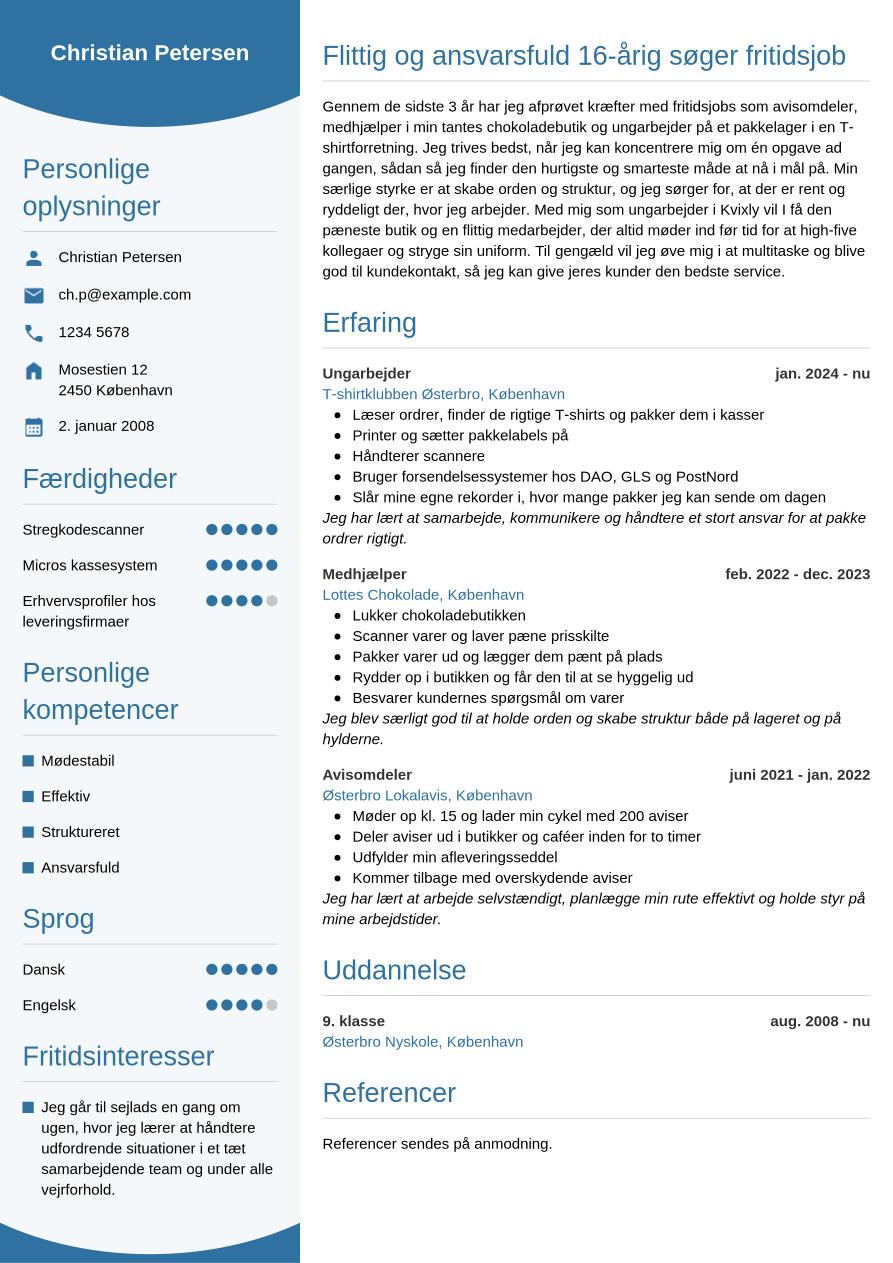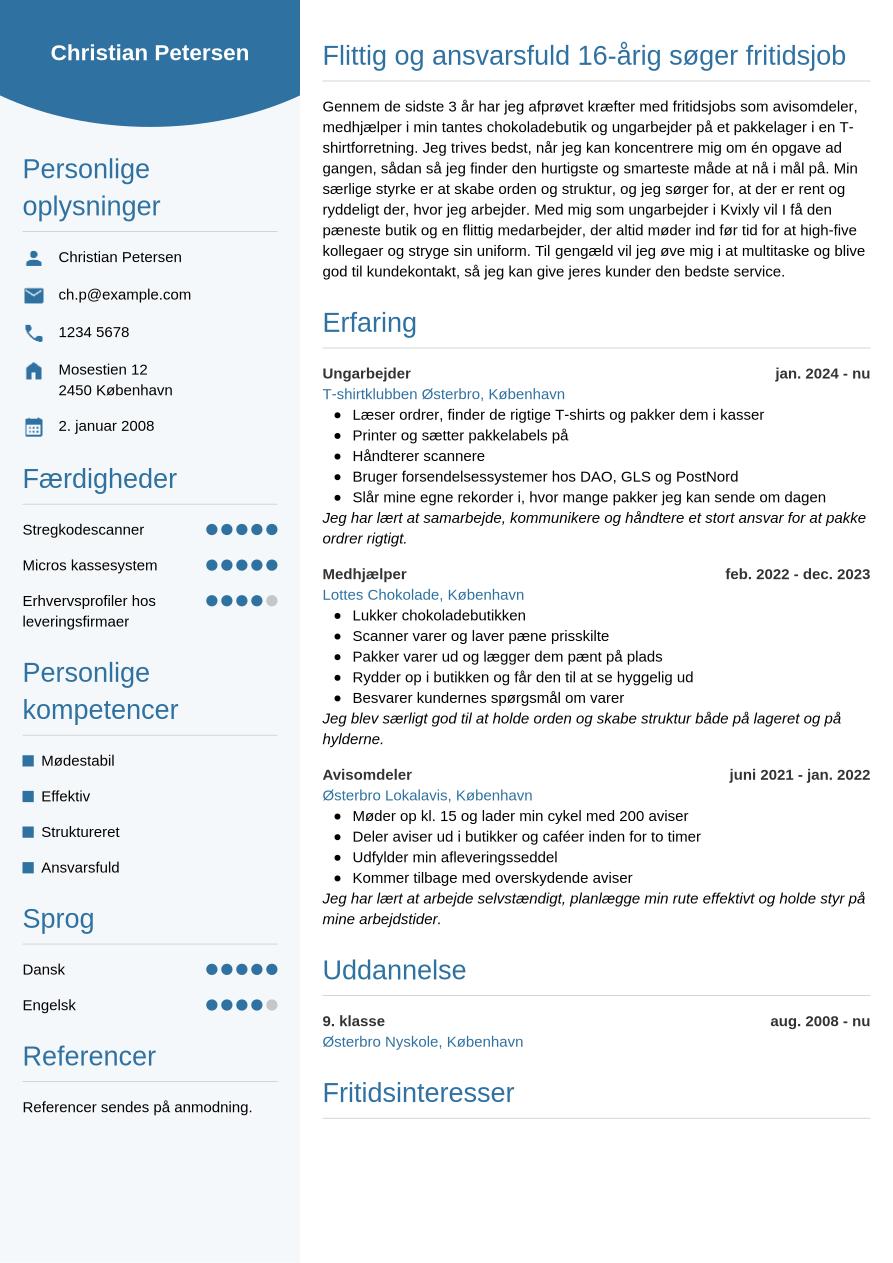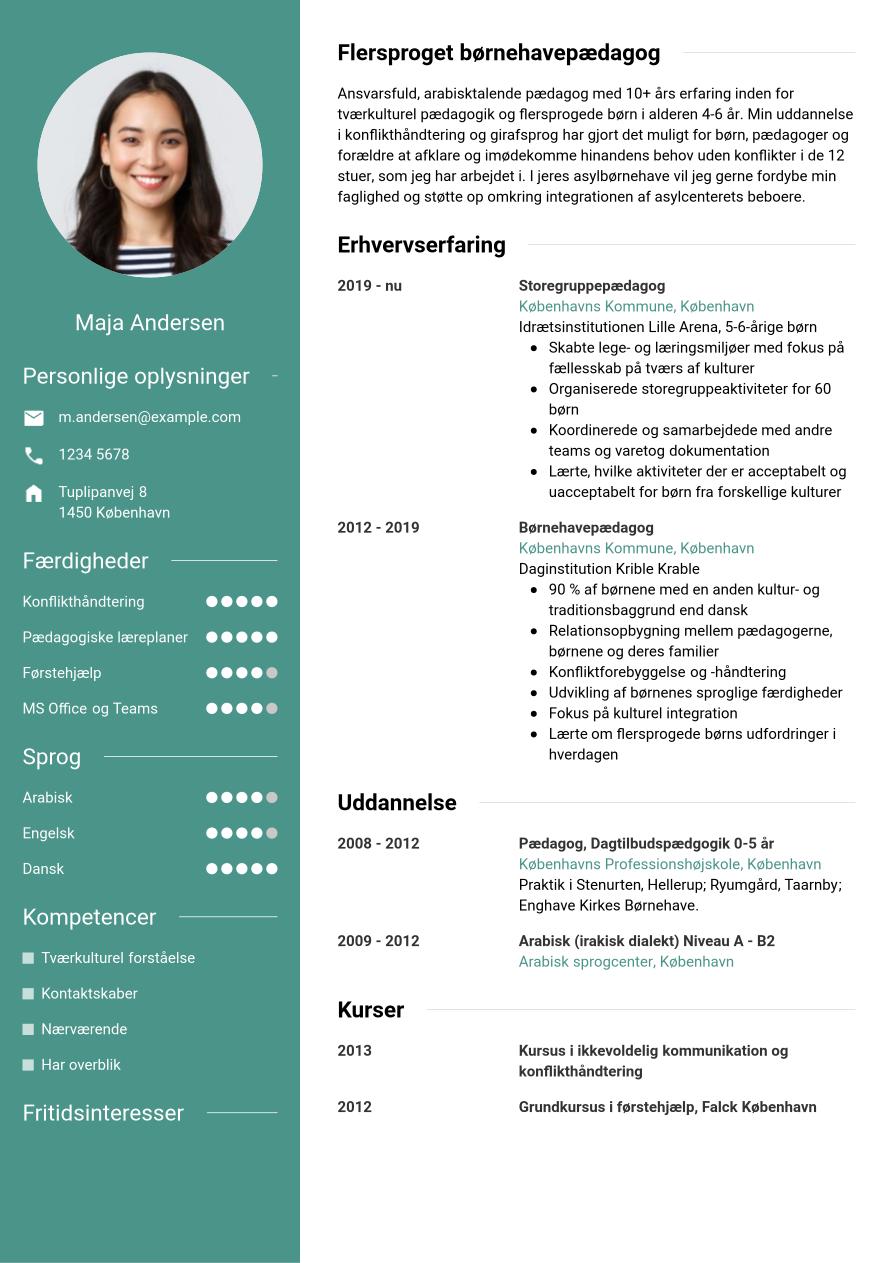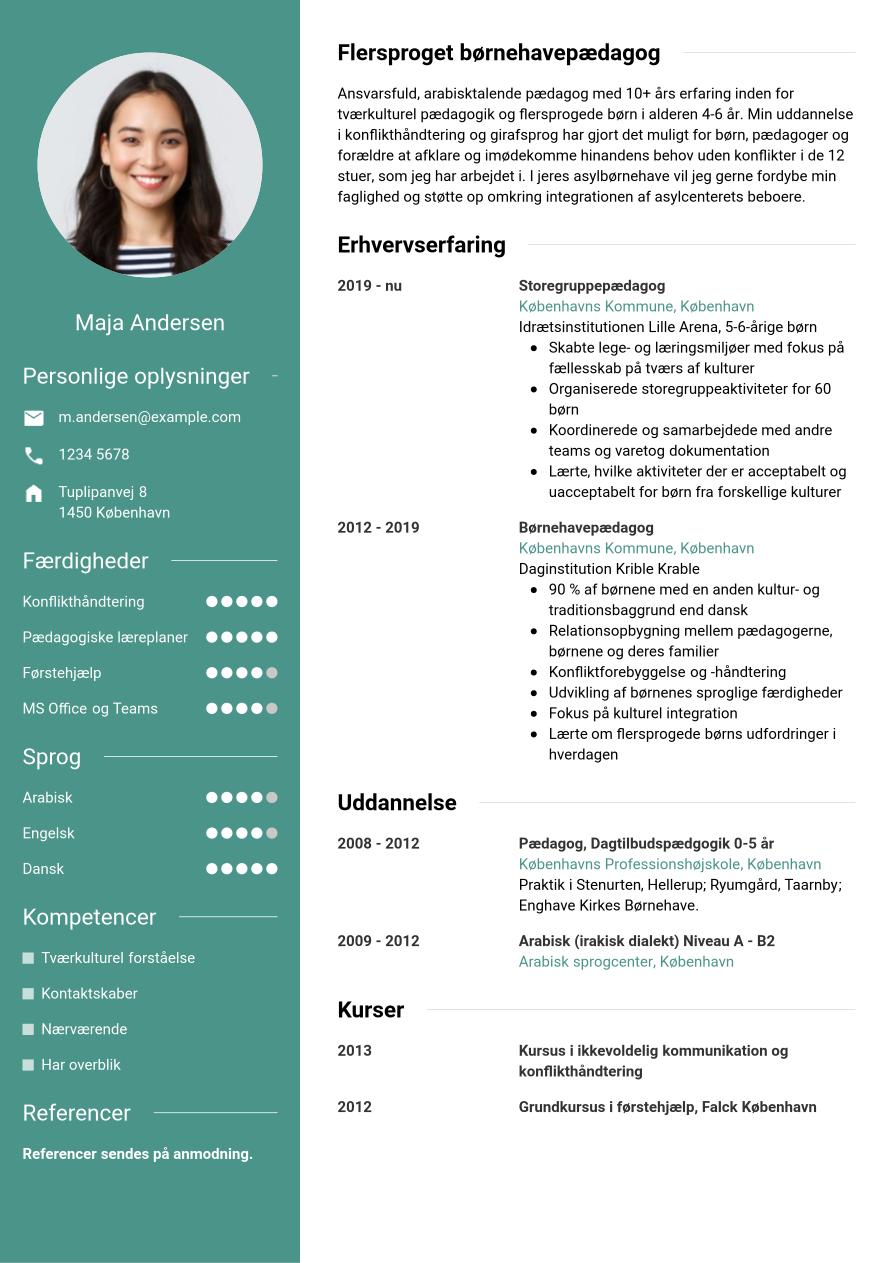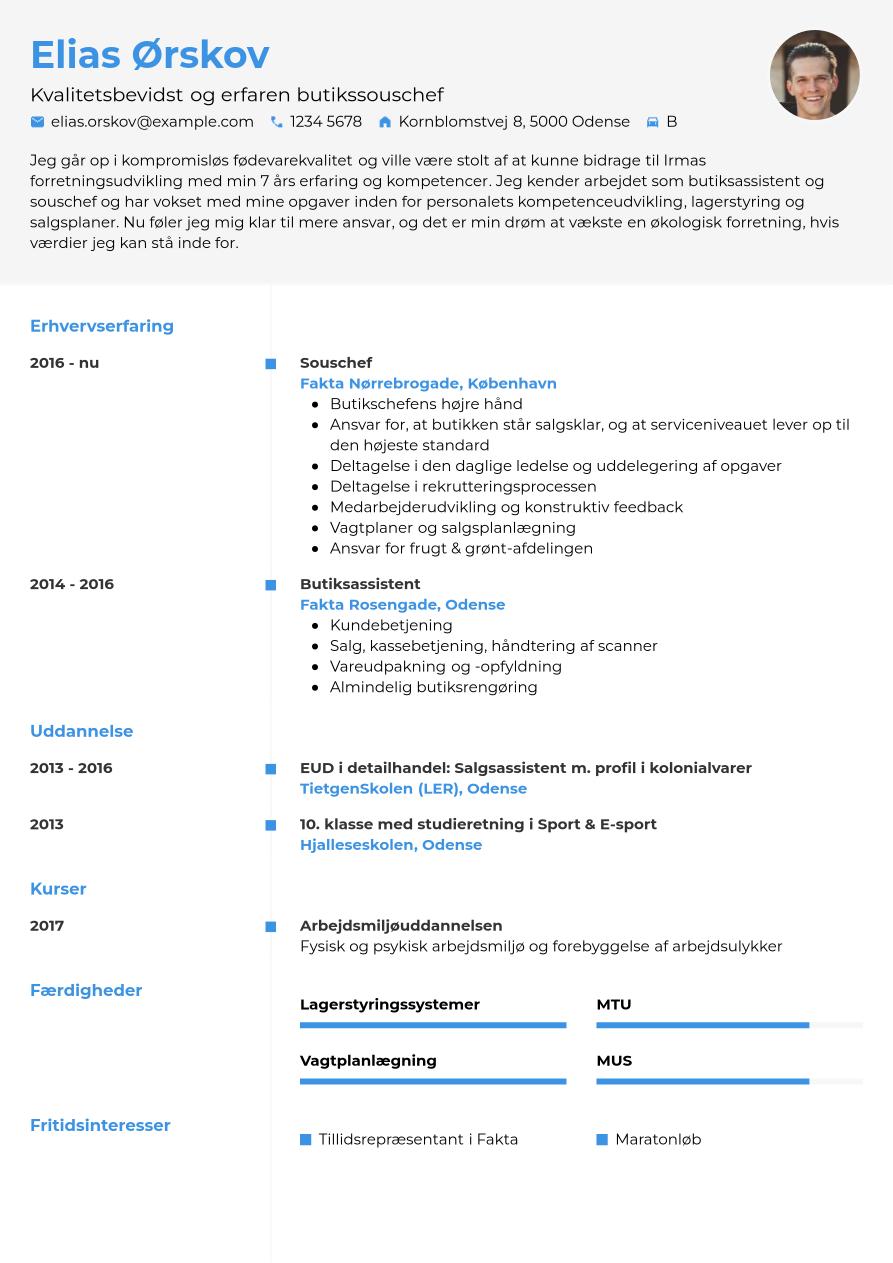
CV-skrifttype: de bedste CV-fonte og typografi
Når du skriver et CV, er der en del overvejelser, som du skal gøre dig omkring typografien. Skrifttypen og skriftstørrelsen samt brug af fremhævninger med blokbogstaver, kursiv eller fed skrift kan gøre ethvert CV kaotisk og svært at læse. På den anden side, hvis du bruger dem fornuftigt og følger nogle simple retningslinjer, kan det forbedre CV’ets læselighed og øge dine chancer for at komme til en jobsamtale. I denne artikel kigger vi på fonte til CV’et samt andre grafiske og typografiske muligheder, du bør overveje, hvis du vil skrive et CV, der virker.
Typografi i CV’et
Når du skal vælge en skrifttype til CV’et, er der to skriftfamilier at vælge mellem: Serif (med ”fødder”) og sans-serif (uden ”fødder). Seriffer er de små linjer, som du kan se under og ved kanterne af bogstaverne i skrifttyper som Times New Roman. Fonte i familien sans-serif er uden de små streger – som den, du læser nu. Når du skriver et CV, bør du vælge én skrifttype, og lave hele CV’et med den. Forskellige skrifttyper skaber nemlig et kaotisk indtryk og trætter læserens øjne.
Serif-fonte til et CV
Serif-fonte er designet med ”fødder” for at øge læsbarheden, når man printer teksten og læser den på papir. Den form for font gør det lettere for læserens øjne at flugte med teksten, og linjerne bliver klare. Disse skrifttyper står i høj kontrast med en hvid, ikke-lysende baggrund. Derfor bliver de brugt i aviser og magasiner, og du kan med fordel bruge dem til printede CV’er. Hvis du gerne vil bruge en serif-font, men er usikker på, om din arbejdsgiver vil læse CV’et digitalt eller på papir, så kan du med fordel bruge skrifttypen Georgia. Den er designet til digital brug.
Sans-serif skrifttyper til et CV
Skrifttyper fra familien sans-serif er åbne og nemme at læse på en skærm. De ser lettere ud, og serifferne forstyrrer ikke øjet, når det hvide baggrundslys fra skærmen skinner bag bogstaverne. Hvis du skal sende dit CV digitalt, så anbefales det at bruge sans-serif-skrifttyper, såsom Arial, Calibri, Verdana, Tahoma og Trebuchet.
Skriftstørrelse på CV
Hvis dit CV skal være nemt at læse, så bør du vælge maksimalt 3 skriftstørrelser af den samme skrifttype: En til overskrifter, en til underoverskrifter og en til brødteksten. Bruger du en åben skrifttype, så kan du med fordel vælge disse skriftstørrelser:
- Maksimalt 16 til overskrifter
- Maksimalt 13 til underoverskrifter
- Maksimalt 11 til brødteksten
Skriftfarve til CV’et
Brug 1 – 2 skriftfarver i et CV, hvis din baggrund er hvid. Den ene farve er til overskrifter, underoverskrifter og brødteksten, og den anden (en lysere skriftfarve) er til de tilfælde, hvor du har to underoverskrifter efter hinanden (se eksemplet i afsnittet om kursiv). Hvis du laver dit CV med margener i en mørkere farve, skal du bruge en tredje skriftfarve til at stå i kontrast med den mørke baggrund. Vælg en hvid eller lysegrå skriftfarve, eller en meget lys tone af dit CV-layouts dominerende farve.
Skrifttypen og kontrast
Da et CV skal fylde maksimalt 2 sider, udnytter man også margener i CV’et for at indsætte vigtig information. Det kan være dit CV-foto, personlige oplysninger, hårde færdigheder, bløde færdigheder samt faglige og personlige kompetencer. Disse margener har oftest en anden, mørk baggrundsfarve. Og det kræver, at din tekst er hvid eller i hvert fald meget lys. Hvis du vælger at bruge margener, så find en passende farvetone til din tekst for at skabe kontrast og øge læsbarheden.
Afstand mellem tekstlinjer i CV’et
For at øge læseligheden af dit CV, brug en større afstand mellem linjerne i brødteksten. Eksempelvis 1,15 pt. kan skabe luft i CV’et og gøre det nemmere at læse. For at gøre det nemt for dig selv, prøv at lave en mockup af dit CV med flere afsnit af erstatningstekst. Markér teksten, og prøv forskellige skrifttyper på den. Når du har valgt en skrifttype, så gør det samme med afstanden mellem linjerne. På den måde kan du afgøre, hvad der ser bedst ud.
Skriftstil til CV’et: Brug af fed skrift
Fed skrift (bold) er iøjnefaldende. Den tiltrækker opmærksomhed og bør bruges til at markere det allervigtigste om dig. Du kan bruge fed skrift både for at markere enkelte ord, hele sætninger og indledninger i sætninger. Sørg for at være konsekvent i din brug af fed skrift: For eksempel hvis du bruger punktopstillinger og markerer starten af sætningerne med fed, så gør det hele vejen for at skabe ensformighed.
Kursiv – Undgå at bruge det i dit CV
Kursiv kan gøre teksten kaotisk, men du kan bruge den i tilfælde af, at du har flere underoverskrifter lige efter hinanden.
Eksempel
UNDEROVERSKRIFT 1: Stillingsbetegnelse – Ansættelsessted – Lokation
UNDEROVERSKRIFT 2: Dato - Dato